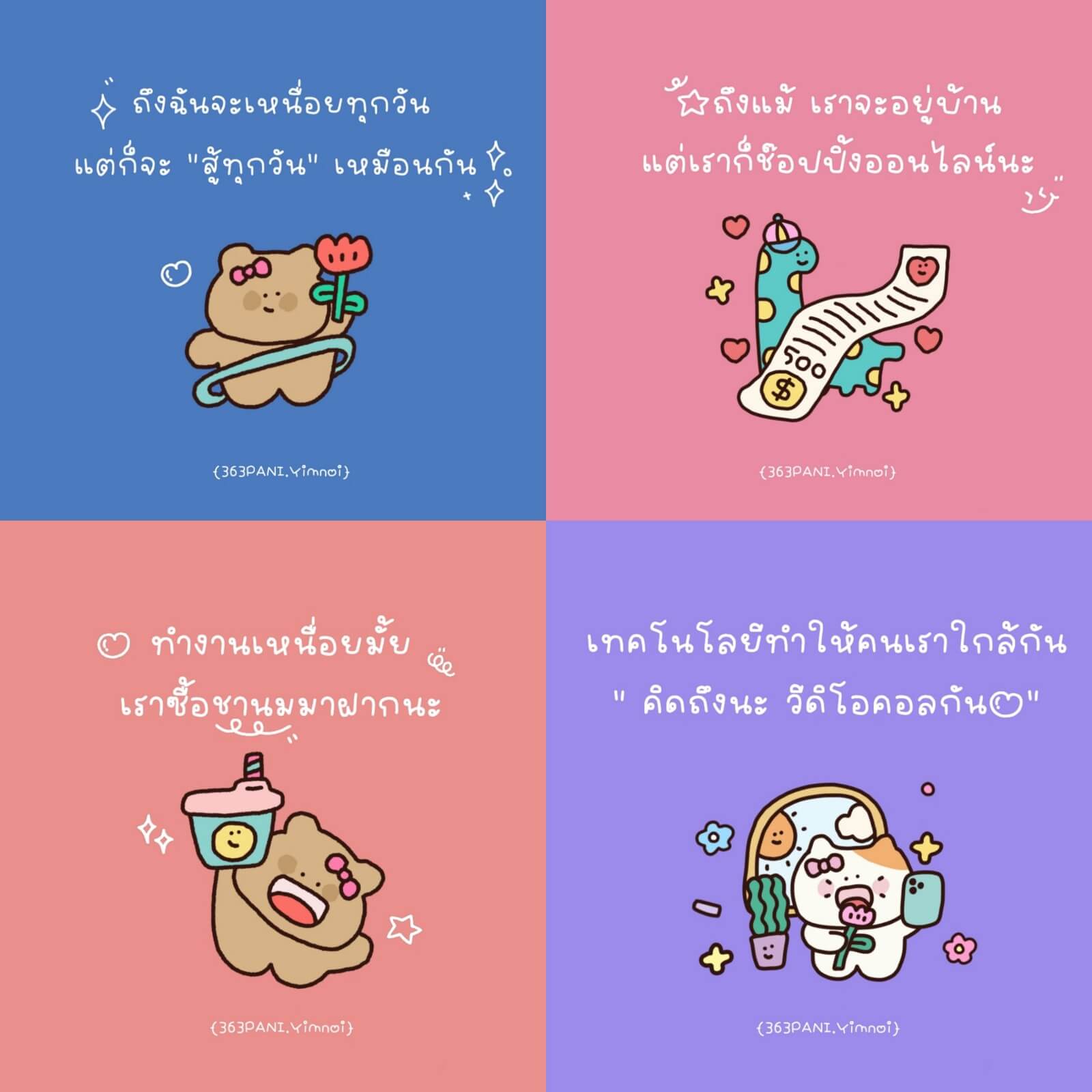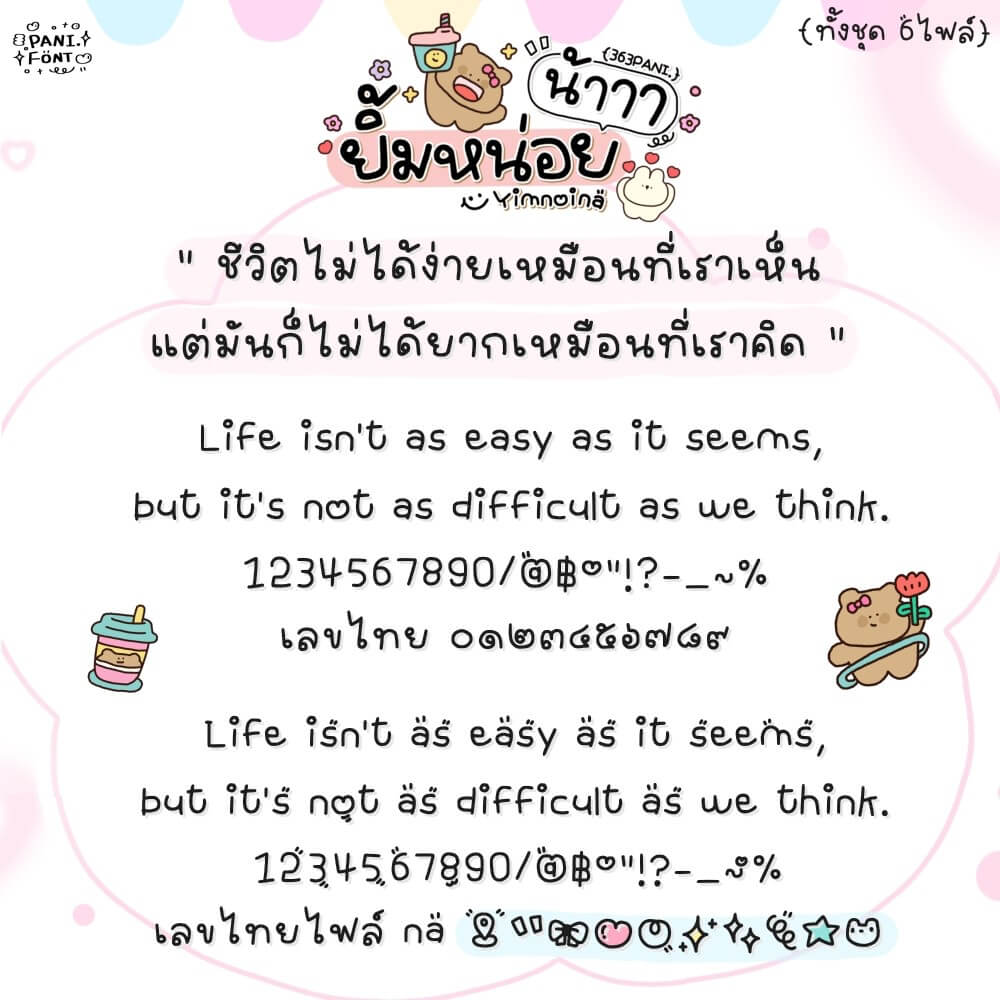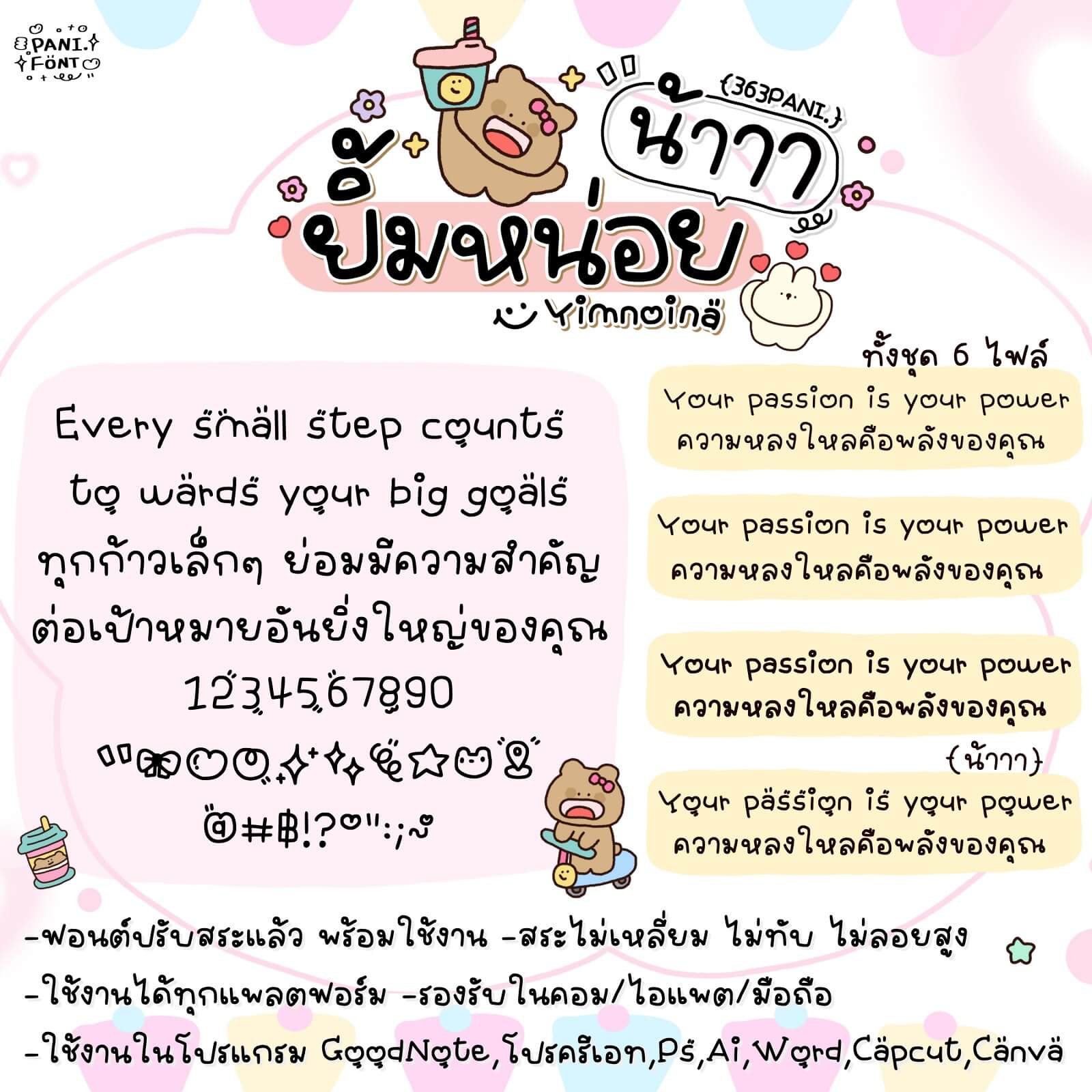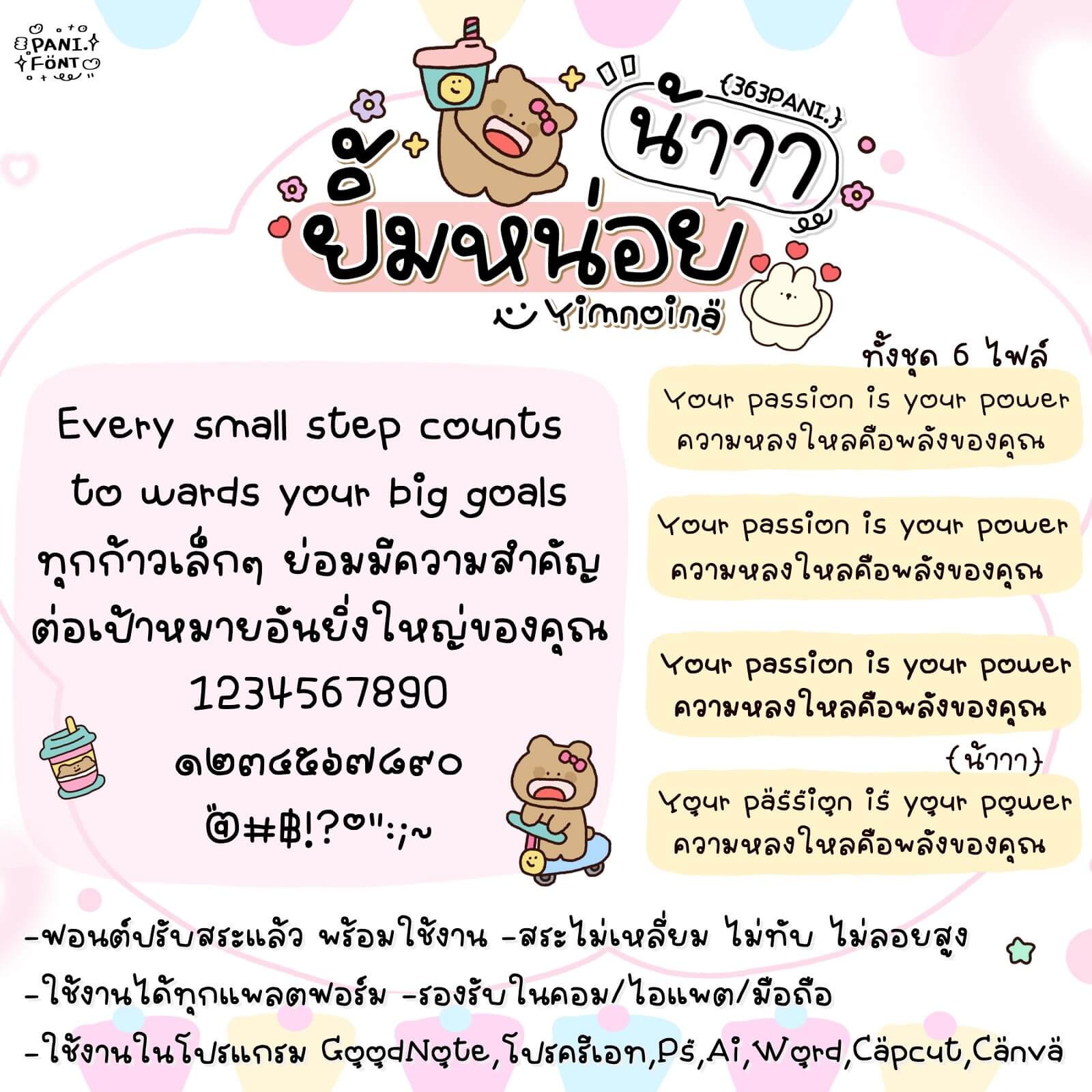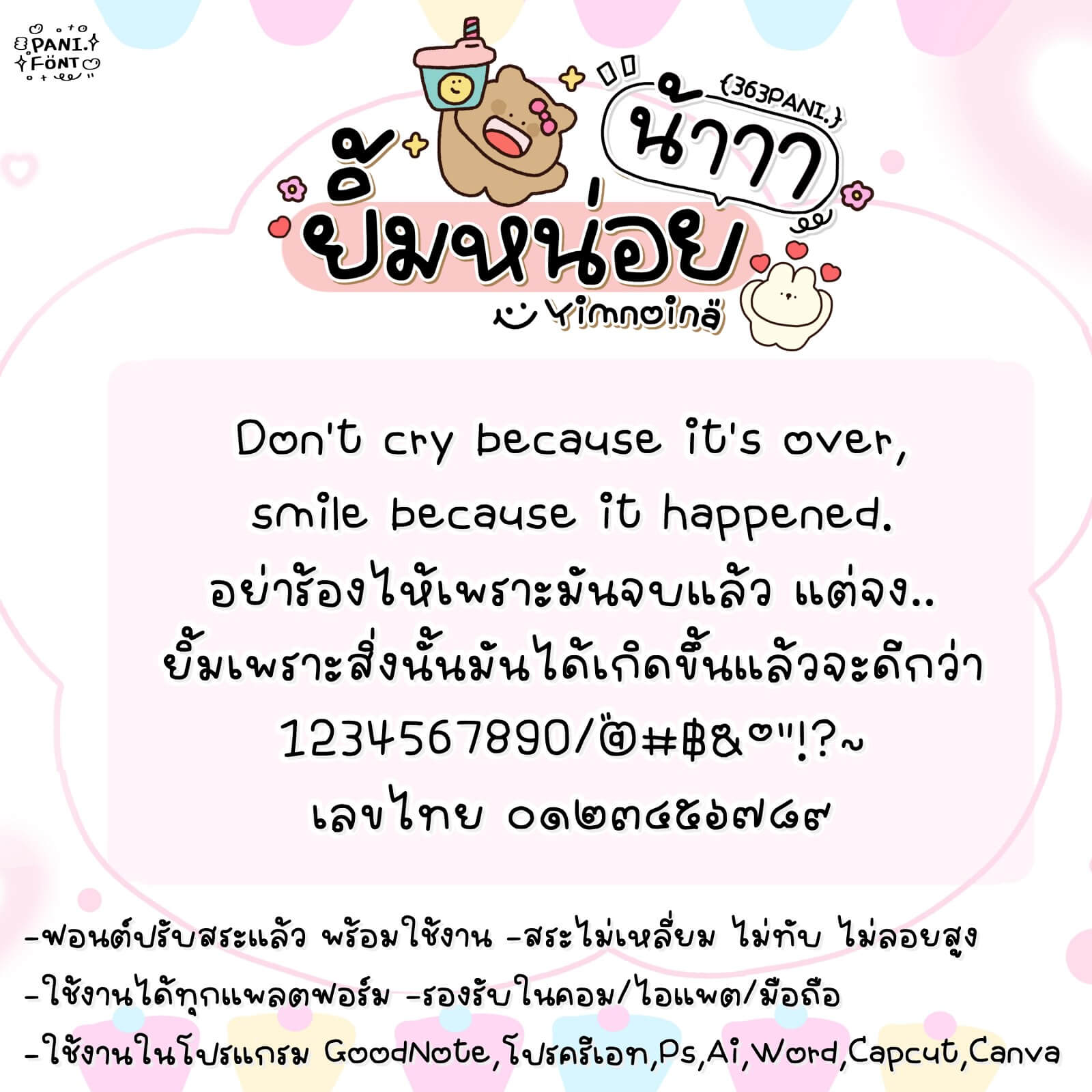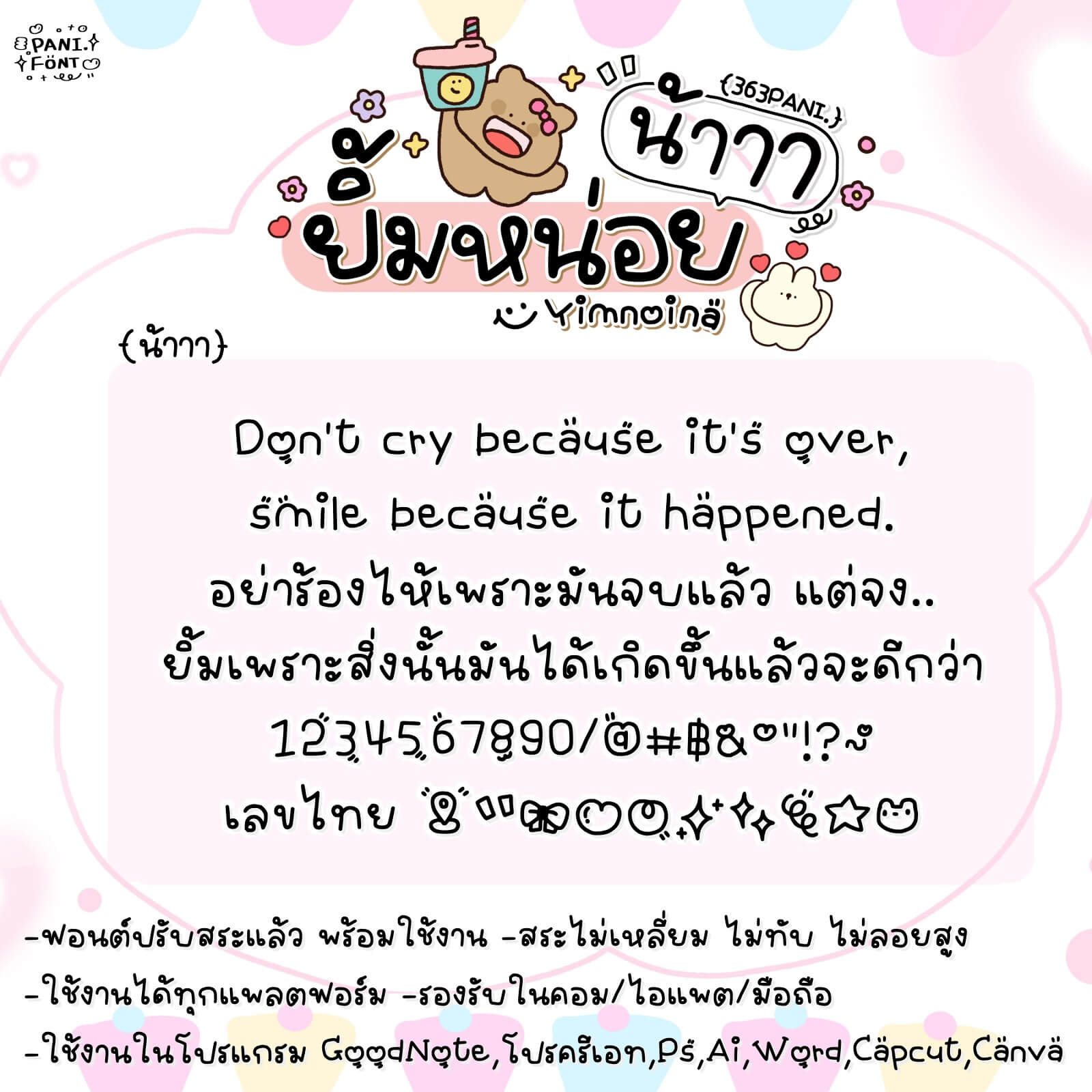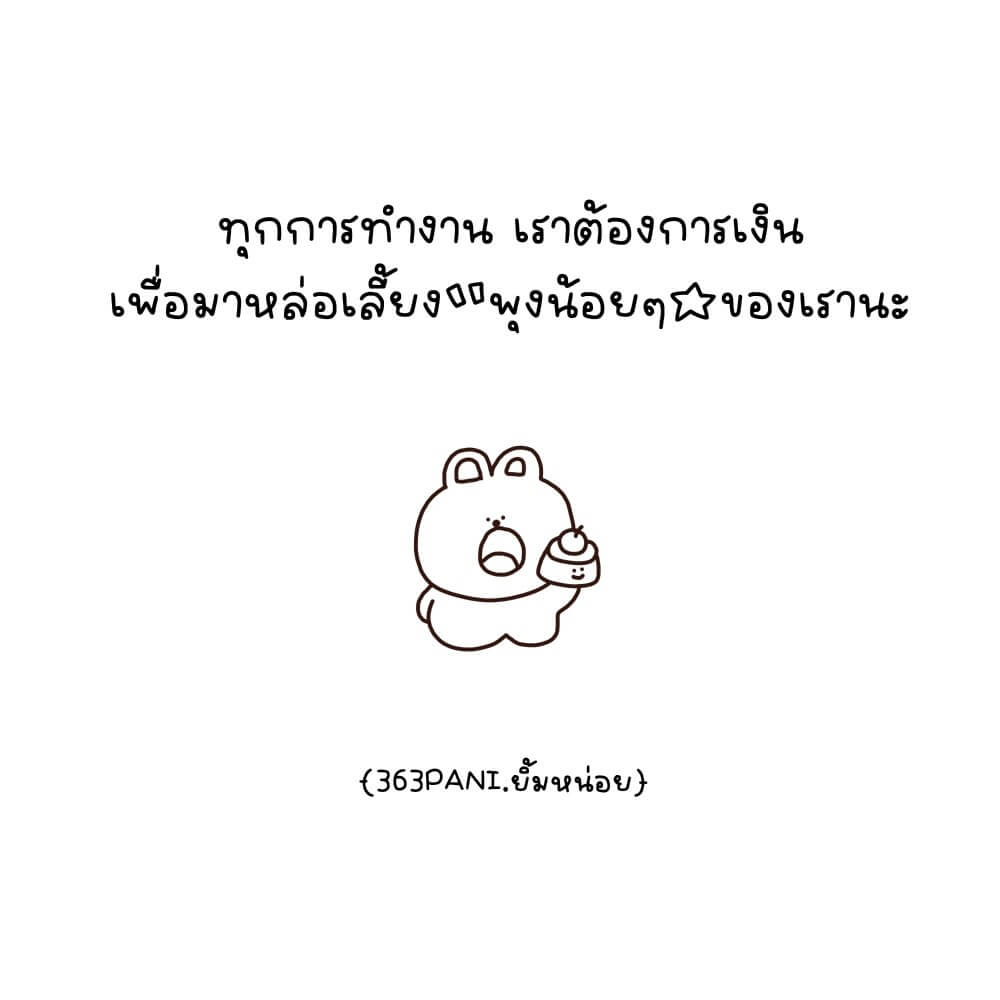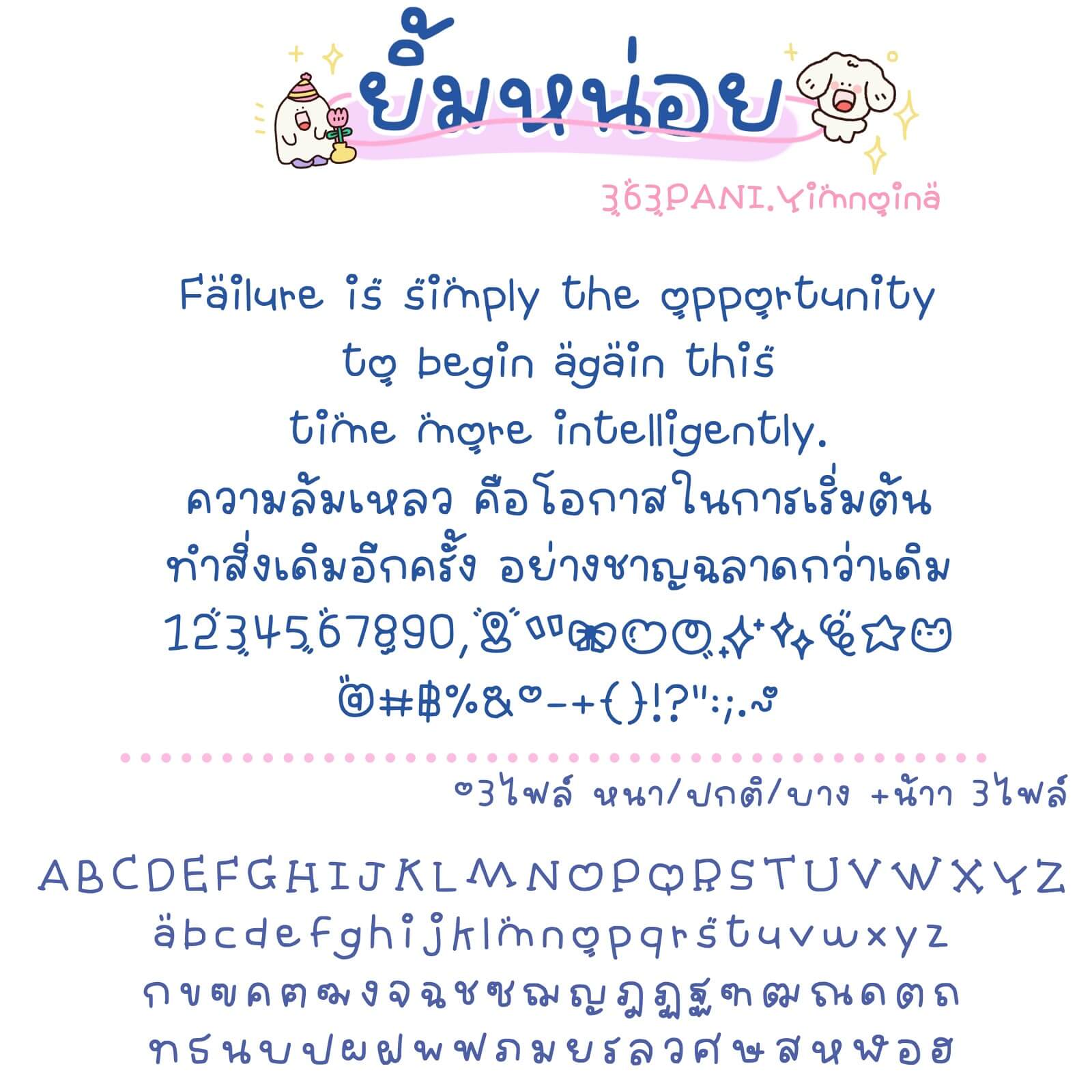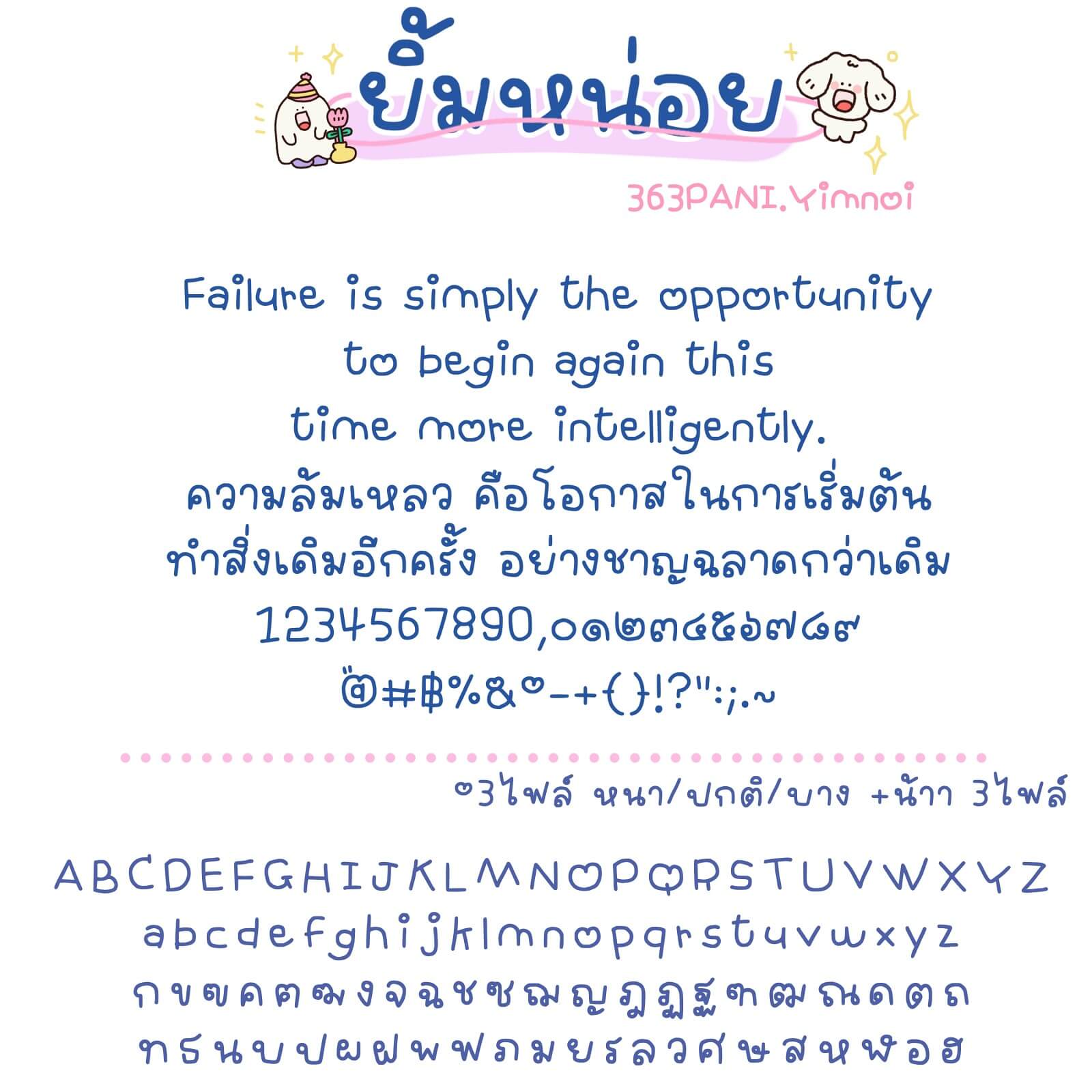
ฟอนต์ 363PANI.ยิ้มหน่อยน้าาา – ตอนเขียนฟอนต์นี้อยากได้ เป็นฟีลคำคม คำใจ เส้นบาง สบายตา แบบอยากได้ฟีลเขียนเอง ตัวไม่เท่ากัน ไม่เรียบร้อย แต่ต้องอ่านง่ายและต้องน่ารัก – ฟอนต์นี้ทำคอนเทนต์สวย ทำคลิป แต่งรูปแนวมินิมัล แนวสดใส ได้หมด
ชุดนี้พิเศษ!! แอนทำให้มีภาษาอังกฤษน่ารัก และเลขไทยเป็นอีโมจิ +เพิ่มให้อีก 3 ไฟล์ ครบน้ำหนัก